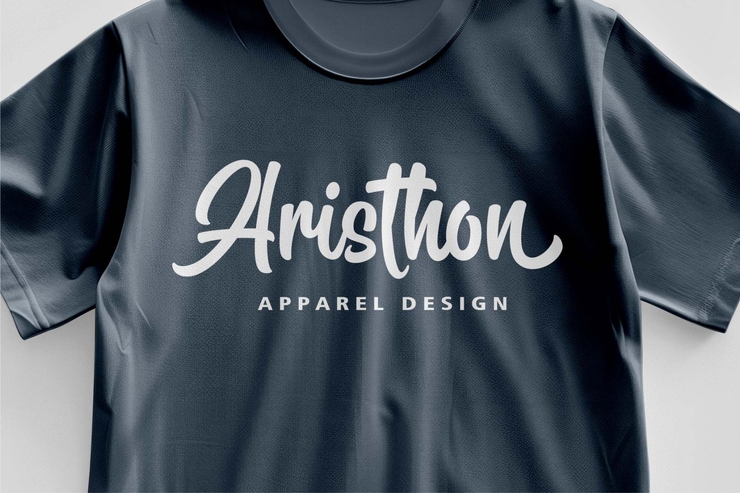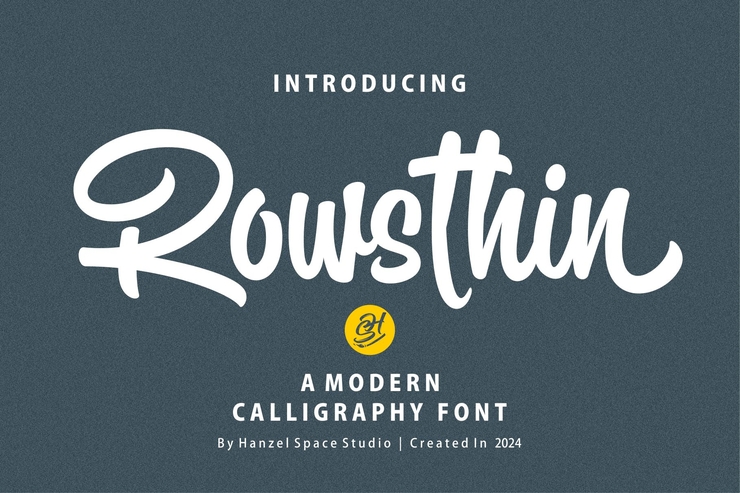
Rowsthin Elegant Dünn Modern Stilvoll Englisch Dekorative Schrift
Rowsthin ist eine raffinierte, dünne, dekorative englische Schrift mit ultradünnen, glatten Strichen und zarten, ausgewogenen Glyphenstrukturen. Ihr minimalistisches, sauberes und leichtes Design bietet einen eleganten, hochwertigen und anspruchsvollen visuellen Stil, der sich ideal für modernes Premium-Branding eignet. Diese stilvolle Schrift eignet sich für Modelogos, Luxusposter, Web-Schlagzeilen, Verpackungen von Schönheitsprodukten, Social-Media-Grafiken und minimalistische dekorative Typografie. Komplett mit Groß- und Kleinbuchstaben ist sie hochgradig skalierbar und lässt sich leicht an Farben, Größen und Layouts anpassen, ohne ihre feinen, dünnen Liniendetails zu verlieren. Geeignet für Grafikdesigner, Luxusmarken und kommerzielle Projekte, um zarte, elegante und auffällige moderne visuelle works.Free für die kommerzielle Nutzung zu schaffen / Kein Copyright 1